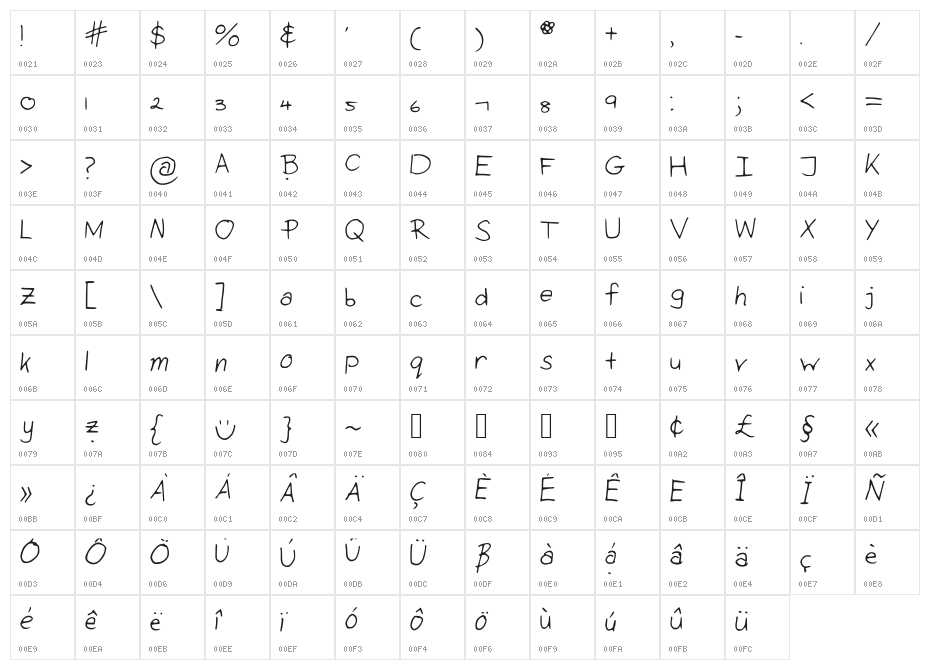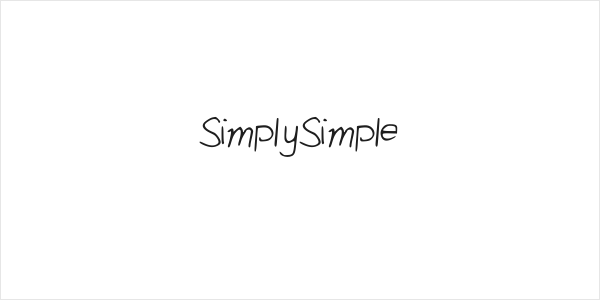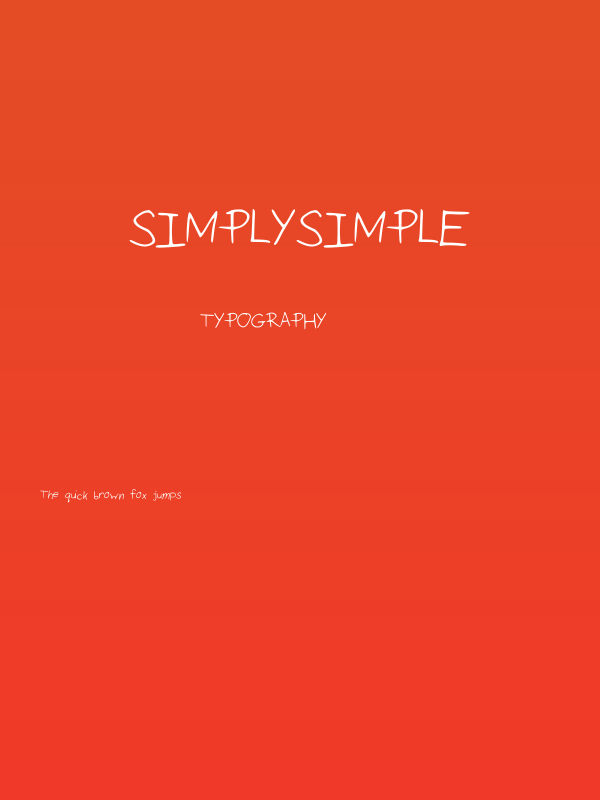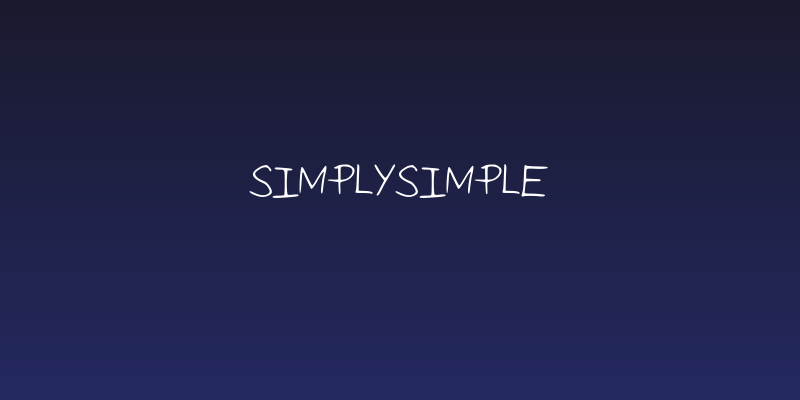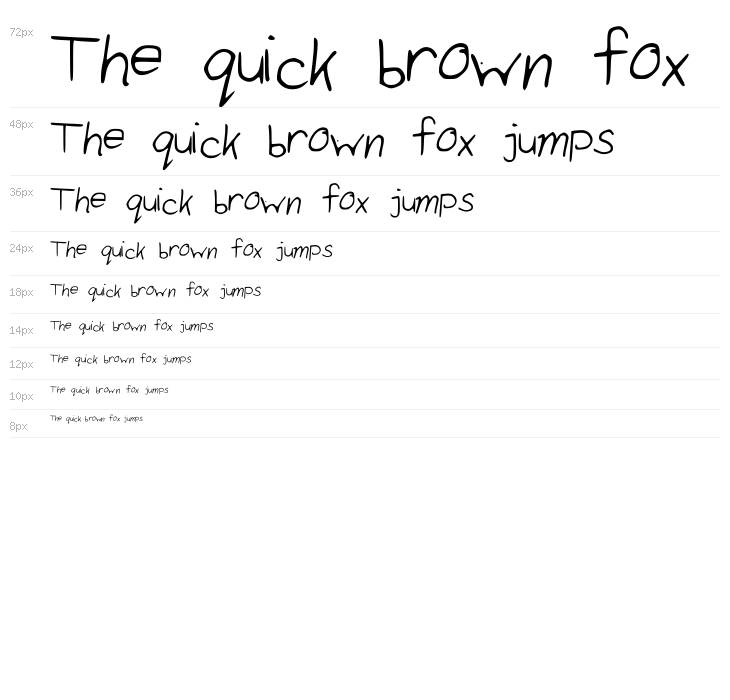
SimplySimple Font
SIMPLYSIMPLE 大文字
SIMPLYSIMPLE 小文字
SIMPLYSIMPLE その他の文字
| 全体的なスタイル | Casual, Playful |
| 用途 | Headlines, Informal text, Creative projects |
| おすすめプロジェクト | Ideal for greeting cards, children's books, creative branding, and informal invitations. |